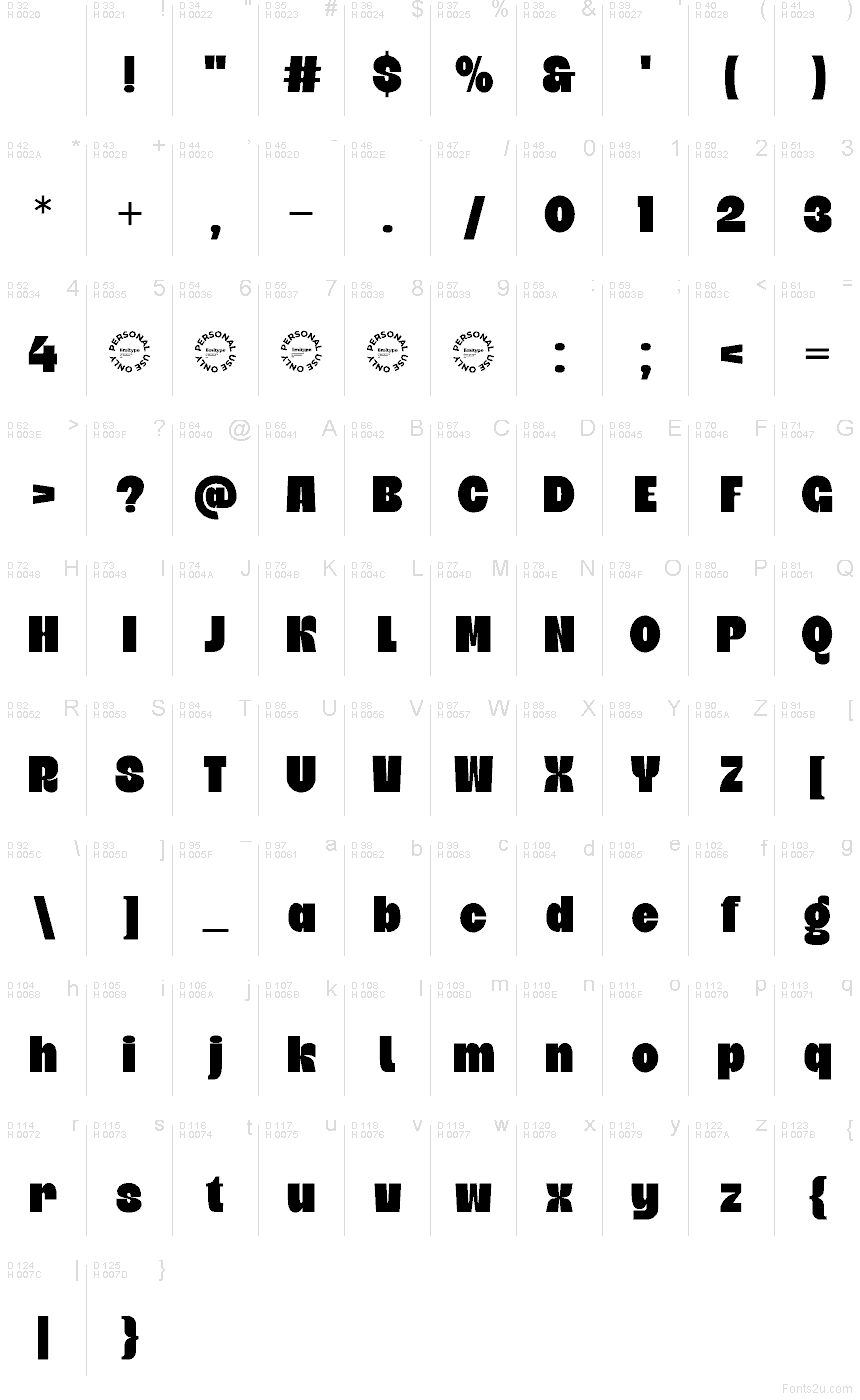
Robold Demo
Robold od Limitype je bezplatné retro display písmo s nezaměnitelným šarmem 70. let. Jeho extrémně tučné, zaoblené litery se tísní v plynulém rytmu, zatímco kompaktní otevřené tvary a jemně sevřené spoje dodávají znakům hravost, nikoliv strohost.
Husté, nafouklé tvary vytvářejí na obalech desek či plakátech festivalů okamžitý typografický blok a dodávají obalům potravin nebo módním grafikám hřejivou, neotřelou vintage náladu. Použijte toto bezplatné písmo, když potřebujete, aby titulek utáhl celou kompozici svou siluetou a nostalgickou energií.